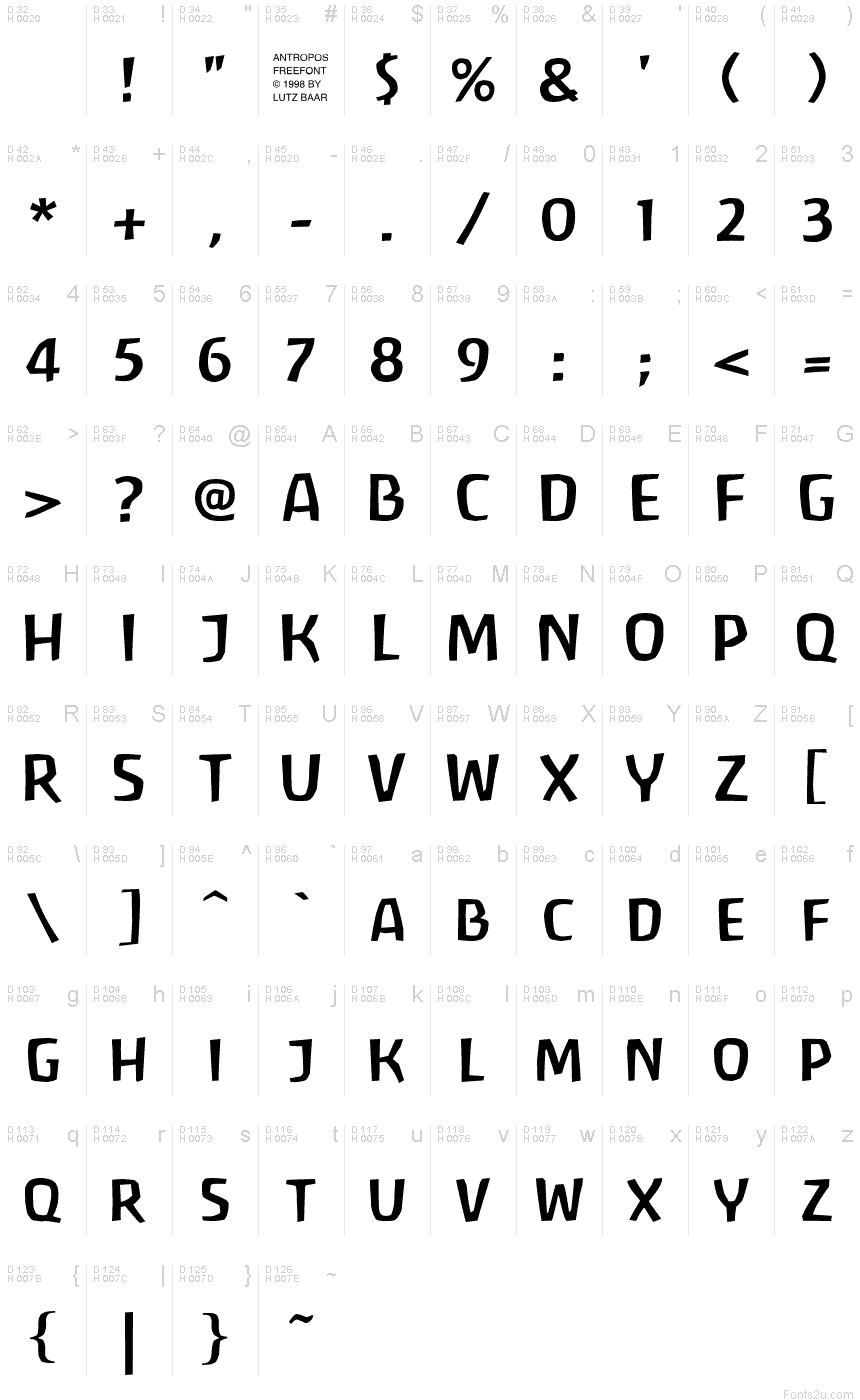
Antropos Freefont od Luth Baar to komiksowy krój pisma typu display, który nadaje nagłówkom ludzki, odręczny charakter. Wysokie, lekko chwiejne litery i nierówne, „atramentowe” krawędzie sprawiają, że każde słowo wygląda, jakby zostało nakreślone grubym flamastrem na papierze. Swobodny, nieformalny rytm nadaje projektom dynamiki, zachowując przy tym czytelność nawet w dużym formacie.
Dzięki Antropos Freefont nadasz surowego, wyrazistego charakteru okładkom komiksów, zinom, plakatom dla dzieci, projektom DIY, miniaturom na YouTube czy tytułom gier niezależnych. Ten darmowy font najlepiej sprawdza się w dużych rozmiarach i pisany wielkimi literami, gdzie jego nietuzinkowe kształty naprawdę błyszczą. W przypadku dłuższych tekstów warto połączyć Antropos z czystym, zaokrąglonym krojem bezszeryfowym, co pozwoli zachować przyjazny i zbalansowany układ.